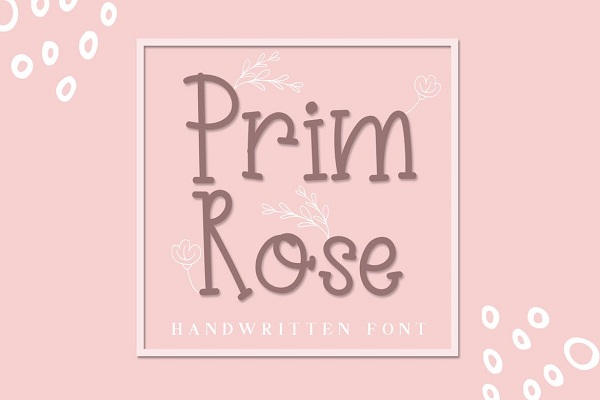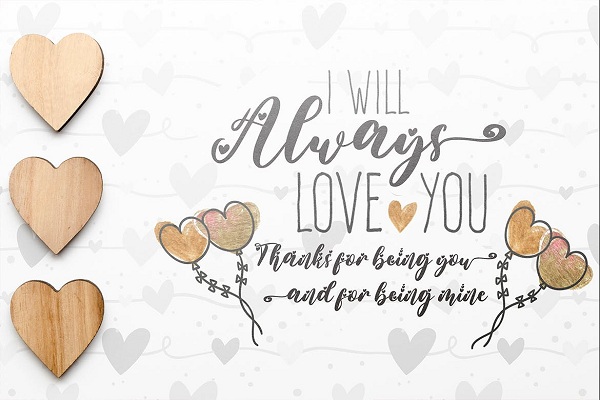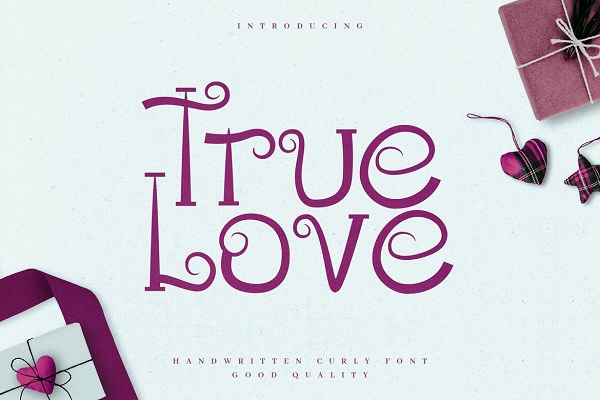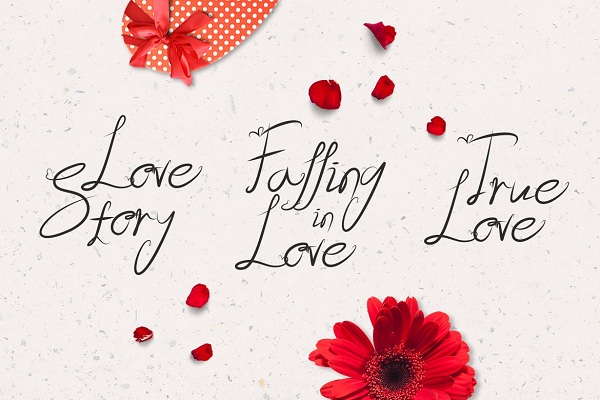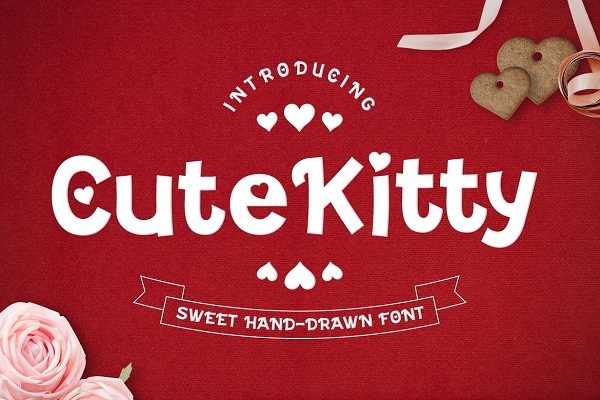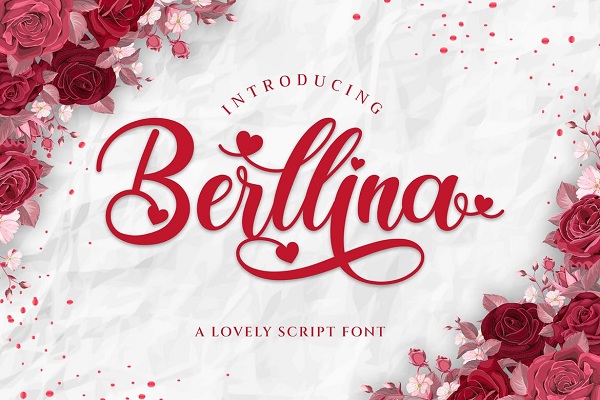
فونت ولنتاین💝دانلود 8 فونت انگلیسی ولنتاین Valentine Fonts
دانلود مجموعه فونت ولنتاین برای طراحی Valentine Fonts
فونت های ولنتاین برای طراحی پوستر،بنر،کارت های عروسی و ...بسیار مورد استفاده قرار میگرند. با توجه به نزدیک شدن روز ولنتاین تصمیم گرفتیم این مجموعه از فونت های انگلیسی را برای شما در سایت قرار دهیم تا در طراحی های خود از آن ها استفاده نمایید.این پکیج شامل 8 مجموعه فونت عاشقانه ولنتاین می باشد که به راحتی بعد از دانلود می توانید از آن ها در فتوشاپ، ورد، ایلستریتور و سایر نرم افزار های دیگر استفاده نمایید.پس اگر برای طراحی های عاشقانه،آلبوم و کارت عروسی،بنر و پوستر های ولنتاین نیاز به فونت های انگلیسی زیبا و فانتزی دارید حتما این مجموعه فوق العاده را از جی اف ایکس دانلود دریافت نمایید.